Splendid
1. Splendid bei Zeilenabständen
»Splendid« ist ein typografischer Fachausdruck aus dem gewerbespezifischen Sprachschatz dspr. Schriftsetzer, Schriftgießer und Drucker aus der Periode des materiellen Schriftsatzes mit physischen Drucktypen aus Metall (z.B. aus einer Blei-Zinn-Antimon-Kupfer-Legierung), Holz (z.B. aus Birnenholz) oder Kunststoff (z.B. aus Kunstharz) für einen sehr weiten Zeilenabstand (ZAB), bei dem das »Durchschießen« aus der Kegelhöhe (siehe Schriftkegel) plus dem »Einraffen« von Blindmaterial bzw. Füllstücken, z.B. Regletten, erfolgt. Auch als »Stark durchschossener Satz« oder »Splendider Satz« bezeichnet.
Etymologisch leitet sich das Adjektiv »splendid« vom lat. »splendidus« für »ansehnlich, glänzend, herrlich« zu lat. »splendere« für »glänzen, strahlen« ab. In der deutschen Sprache primär als Synonym für »prächtig«, »freigebig« und »großzügig« verwendet.
In der digitalen Typografie bzw. im DTP Desktop Publishing wird der Terminus »Splendid« für einen sehr weiten Zeilenabstand verwendet, der etwas bis signifikant großzügiger ist, als der durchschossene Zeilenabstand, also der normale ZAB.
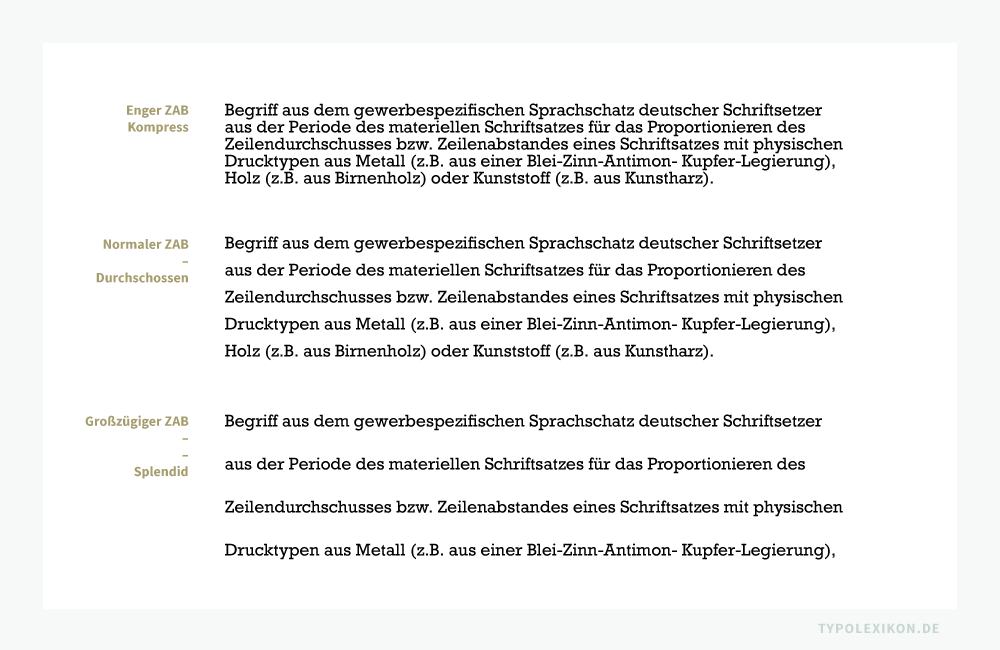
Der Zeilenabstand beeinflusst den Grauwert und somit die Lesbarkeit eines Schriftsatzes. Ab wann ein splendider Zeilenabstand – im Sinne der Lesetypografie – zu weit gerät und somit die Lesbarkeit beeinträchtigt, hängt von der verwendeten Schriftart, dem Trägermaterial, der Farbe bzw. dem Layout ab. Die Wahl des geeigneten Zeilendurchschusses gehört in das Segment der Mikrotypografie.
2. Splendid im Schriftsatzlayout
In der Typografie wird ganz allgemein ein offenes, großzügiges und geräumiges Layout bzw. ein Buchsatzspiegel oder ein Gestaltungsraster mit weiten Zeilenabständen und viel unbedruckter Fläche (z.B. breite Bund-, Kopf-, Fuß- und Außenstege), als »Splendider Satz«, »Splendider Satzspiegel« oder »Splendides Layout« bezeichnet.
Der Typograf und Schriftgestalter Paul Renner (1878–1956) beschreibt 1940 den Splendidsatz wie folgt: 1)
(…) stark durchschossener Satz, aber auch ganz allgemein das, was der Laie Papierverschwendung nennt, also auch besonders breite Papierränder, Anfangskolumnen mit reichlichem Vorschlag und dergleichen.
Die splendide Gestaltung eines Buches ist keine Erfindung der Typografie. Sie wurde bereits in der frühgotischen Kalligraphie angewandt, beispielsweise in Form des Villardschen Teilungskanons bei Folianten.